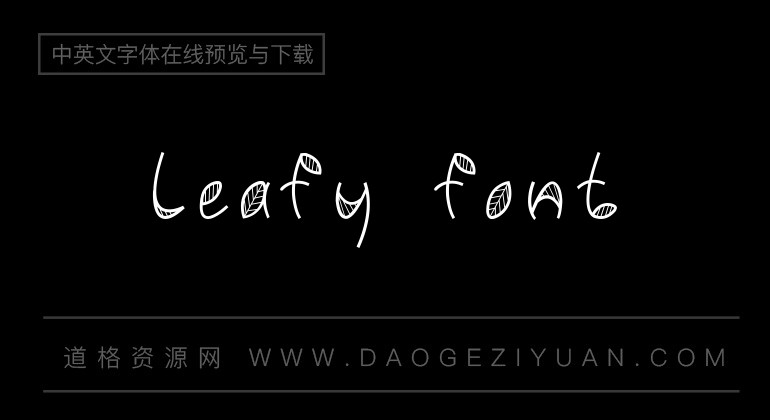
Leafy font
Leafy font是一种手写风格的字体,其设计师是来自印度的Anis Iqbal。这种字体的特点是在字母的末端和拐角处有一些绿色的叶子装饰,让字母看起来更加生动和有趣。 Leafy font的设计灵感来自于自然界中的植物和树木,这种字体适合用于与自然、环境和健康有关的品牌,比如药品、有机食品、绿色能源等等。此外,这种字体也可以用于卡片、海报、T恤印刷等艺术设计类的项目中,为作品增加一些独特的视觉效果。 总的来说,Leafy font是一种非常有趣和具有视觉吸引力的字体,它的设计灵感来自于自然界,适用于多种应用场景。
Leafy font是一款非常不错的手写艺术字体,具有很好的视觉感,适合于文化类的宣传设计、商业类品牌的广告和产品包装设计以及个性化文字排版等较多场景。